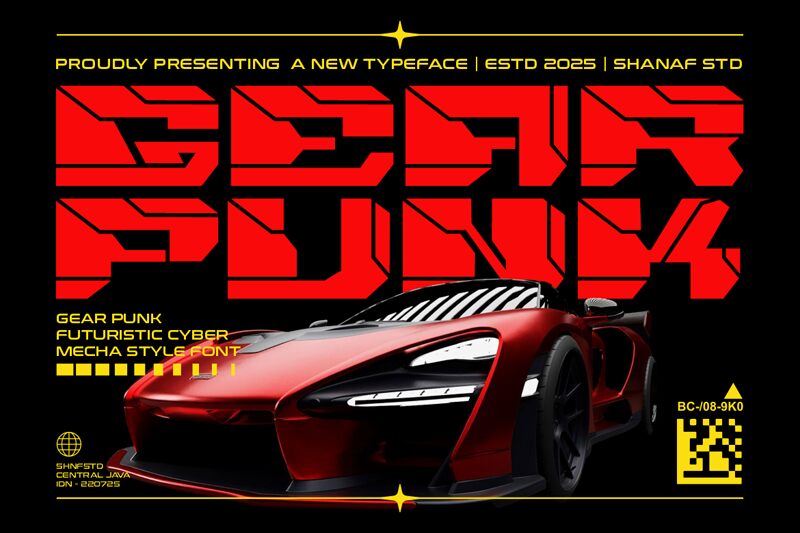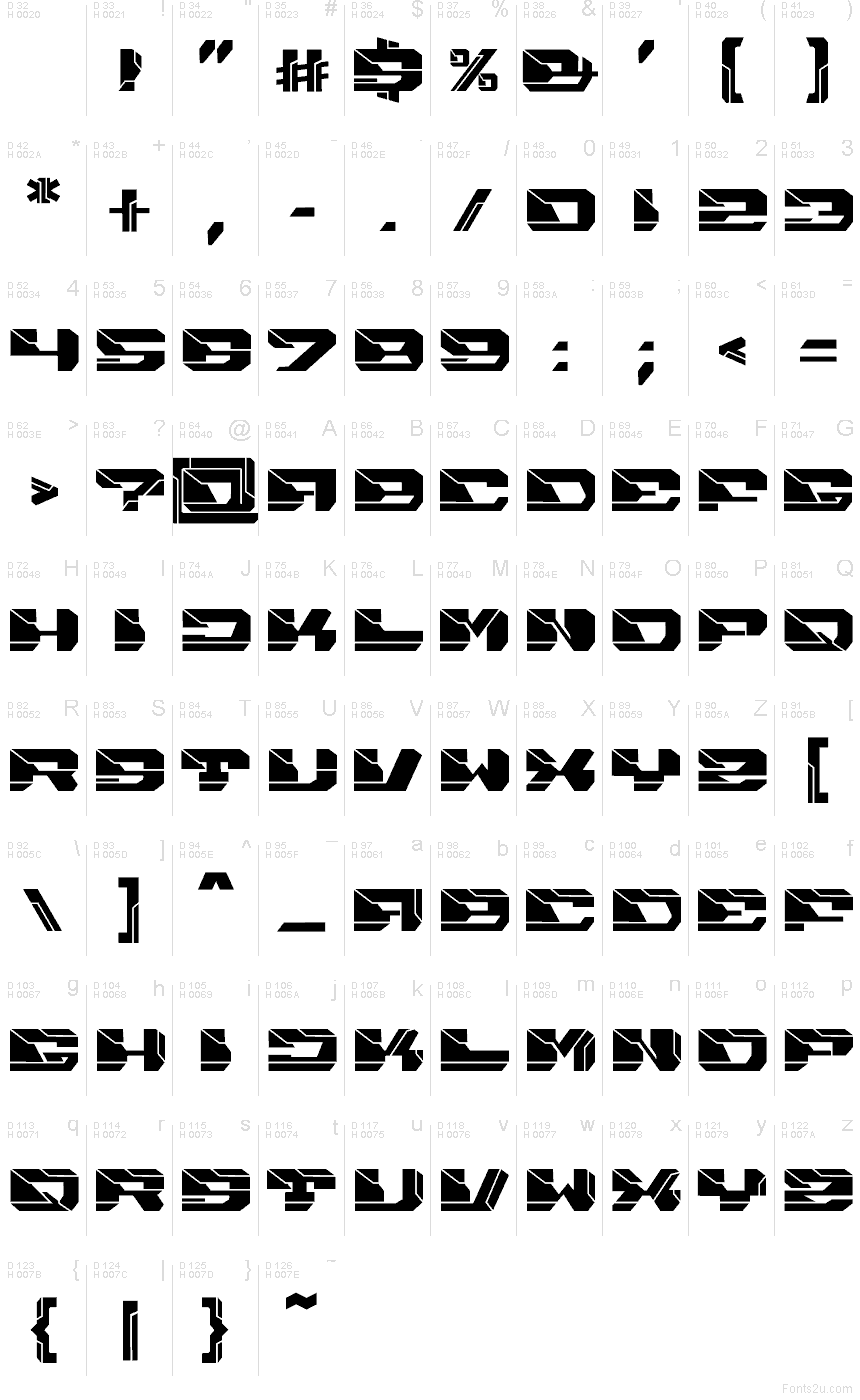
Gearpunk od Shanaf Studio to darmowy, futurystyczny krój pisma typu display o surowym, industrialnym charakterze. Litery oparte są na masywnych, geometrycznych blokach i ostrych, diagonalnych cięciach, co nadaje alfabetowi modularny rytm w stylu science-fiction, przypominający bardziej metalowe panele czy znaki techniczne niż klasyczne liternictwo.
Font naturalnie wpisuje się w logotypy gier, plakaty technologiczne, okładki albumów, napisy oraz opakowania, wszędzie tam, gdzie potrzebujesz wyrazistego, syntetycznego brzmienia bez popadania w generyczne cyber-stylizacje. Dzięki konstrukcji opartej na szerokich formach, ostrych kątach i ściętych narożnikach, Gearpunk najlepiej sprawdza się w krótkich nagłówkach, odznakach i monogramach, gdzie ta techniczna sylwetka może w pełni wybrzmieć.